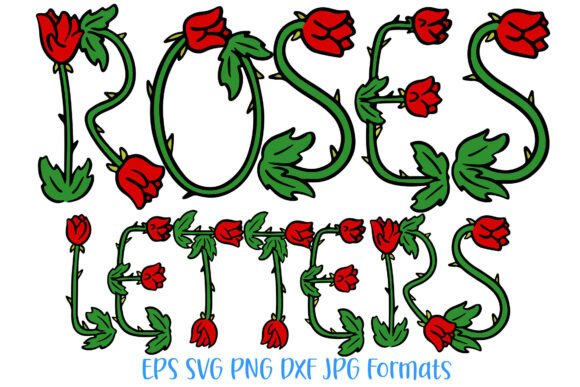
Roses Letters Font Spring Flower Doodle
Якщо ви шукаєте високоякісні ресурси, такі як Roses Letters Font Spring Flower Doodle, цей преміум-пакет є фантастичним вибором для ваших творчих проектів.
Створений з високою точністю, Roses Letters Font Spring Flower Doodle забезпечує чисті вектори, плавну типографіку та комерційну ліцензію для вашого спокою.
Незалежно від того, чи створюєте ви продукти POD (друк на вимогу), весільні запрошення або графіку для соціальних мереж, Roses Letters Font Spring Flower Doodle стане ідеальним вибором.